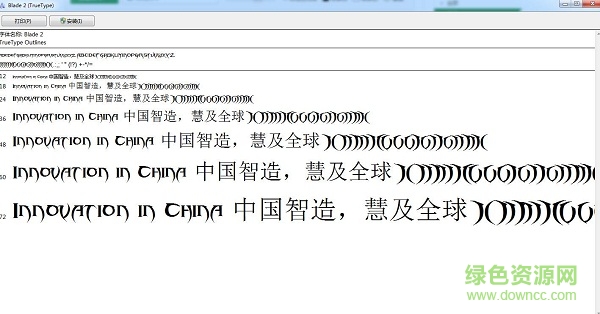
blade 2 regular
blade 2 regular字體是一款剛?cè)岵?jì)的英文個(gè)性字體,字體線條犀利,干凈利落,給人新銳奪目的感覺(jué),可以用在產(chǎn)品包裝設(shè)計(jì)、海報(bào)設(shè)計(jì)等方面,不歡迎大家在綠色資源網(wǎng)下載!